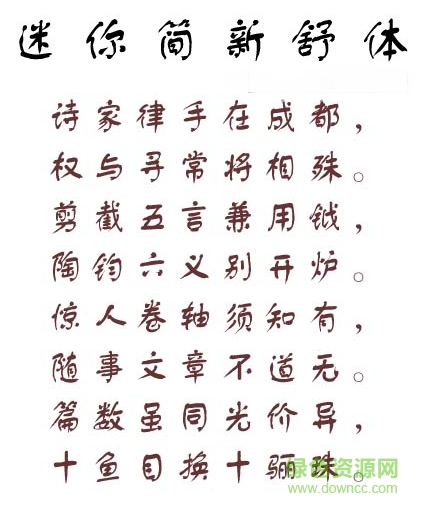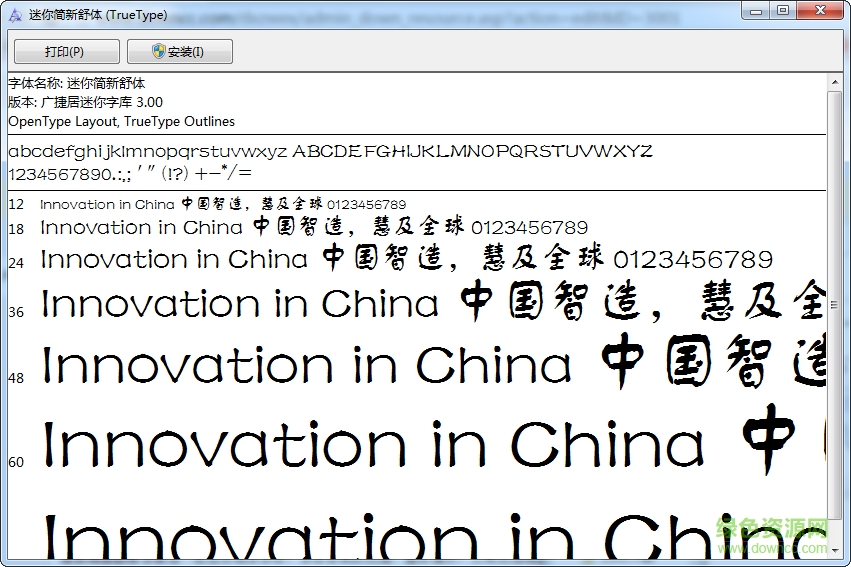
迷你簡新舒體字體是一款迷你簡體字體,字體非常的優(yōu)雅,整體偏長,又有點加粗的意味,祈禱了非常醒目的效果,非常適合廣告、報刊雜志等的印刷,喜愛的朋友趕快到綠色資源網(wǎng)下載體驗吧!
字體樸實端正,筆法舒展有力,流暢自然,結(jié)構(gòu)勻稱,適
用于書、報、雜志和各級教材中的小標(biāo)題及正文字。
字形修長秀美,平正端慶,線條婉轉(zhuǎn)流暢,骨力內(nèi)涵,
挺拔勁健,具有很高的實用性和欣賞性。該字體實用性
強,注重篆法的正確和規(guī)范,注重字形美觀和風(fēng)格的統(tǒng)一。
其特點是端莊中含瀟灑,凝重中寓自然,字體簡潔明快、
流暢大方、簡繁齊備、雅俗共賞,更接近人們的生活,實
用性很強,特別適用于書寫信函、報告、文章等。